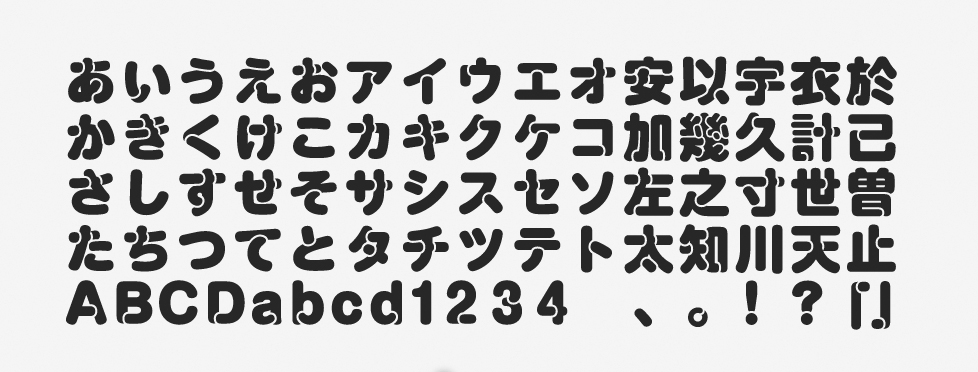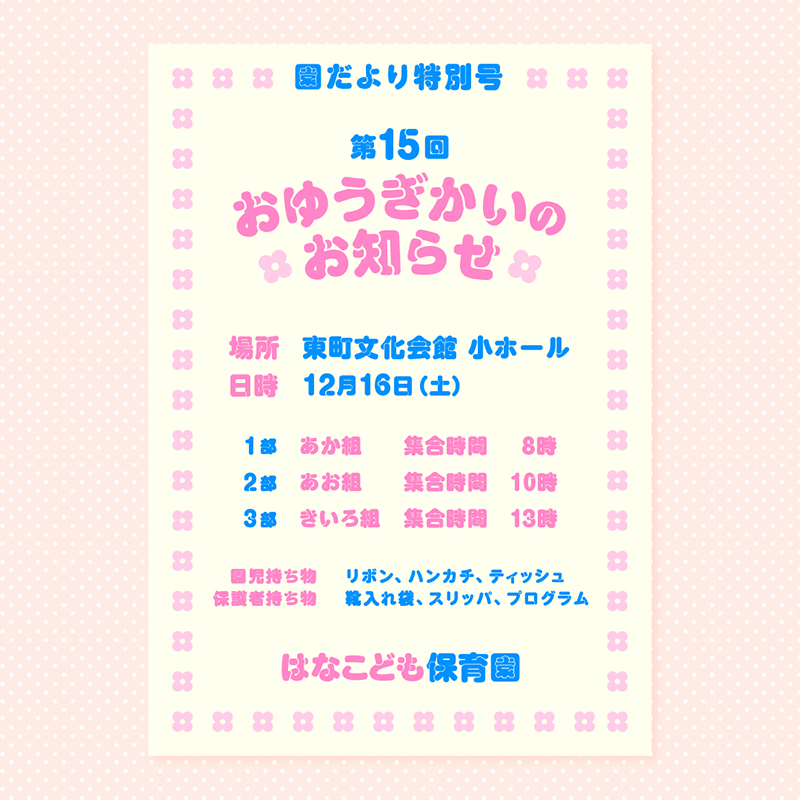
「トンネル」について
トンネルは2013年に登場したフォントです。2023年の秋には、和文・欧文ペアカーニングと最新のIVSに対応したAP版フォントとしてもリリースされました。線画の重なる部分を食い込ませ、文字が立体的に見えるようにデザインされたフォントです。やや幼い印象で目を引きやすいため、特に子ども向けのシーンで活用されています。
「トンネル」の特徴
独特な立体感とともに、極太の丸ゴシック体をベースとした可愛らしさも魅力です。コミックやチラシのように、強いインパクトやポップな印象が必要とされるデザインで、高い効果を発揮します。
文字そのものの線の太さ(ウエイト)は1種類ですが、食い込みのための白いラインに「細線(Tighline)」と「太線(Wideline)」の計2種類があります。全体的には太めのフォントであるため、タイトルや見出しなど大きめのサイズでの使用がおすすめです。
このフォントは立体感が面白く、まるで1文字1文字が愉快なキャラクターのようにも見えてきます。楽しい表現をしたい場合には、かなりの威力を発揮するでしょう。一般的な丸ゴシック体と併用しても面白く、コミックや絵本などでも見かけることが多いフォントです。